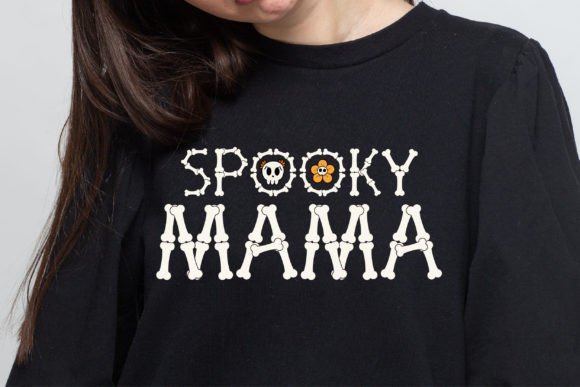
Halloween Bone Font
Halloween Bone Font – الخط المثالي لأجواء الهالوين! ????????
اجعل تصاميمك أكثر رعبًا وجاذبية مع Halloween Bone Font، الخط الفريد المصمم على شكل عظام لإضفاء طابع مرعب ومميز على مشاريعك.
???? المميزات:
✔ تصميم مستوحى من العظام يناسب أجواء الهالوين والمناسبات المخيفة.
✔ مثالي للتصميمات الجرافيكية، الدعوات، التيشرتات، الشعارات، والإعلانات.
✔ جودة عالية مع تفاصيل دقيقة تضيف لمسة إبداعية إلى أعمالك.